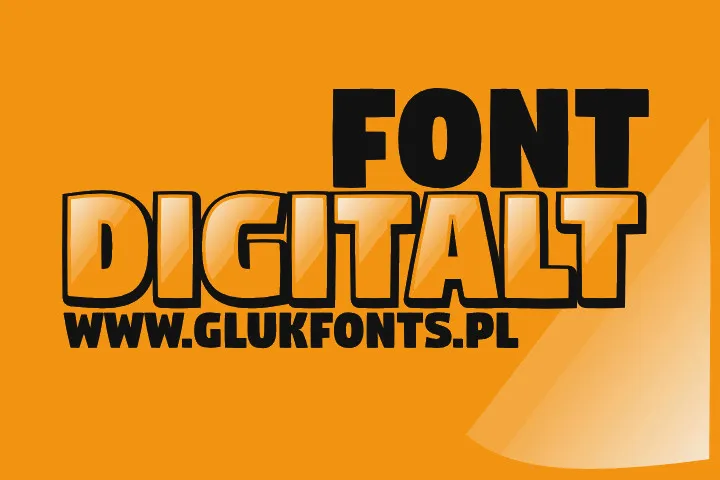
Digitalt Font – Download Grátis
A Digitalt Font é uma elegante fonte em estilo gera, criada pelo designer Hamilton, especialmente adequada para aplicações digitais modernas. Suave e arredondada enquanto mantém a eficiência de um tipo digital, ela traz ao seu design o equilíbrio perfeito entre praticidade e sofisticação. Ideal para usar em sites web, aplicativos móveis ou qualquer outra plataforma digital que exige uma fonte com agilidade e facilidade de leitura, Digitalt traz à sua marca uma cara moderna e contemporânea, sem perder o toque personalizado necessário para um bom design. Acompanhada de regras claramente explicadas em inglês, a Digitalt Font é uma escolha ideal para quem busca uma fonte que se destaca enquanto atende às necessidades funcionais do design digital moderno.